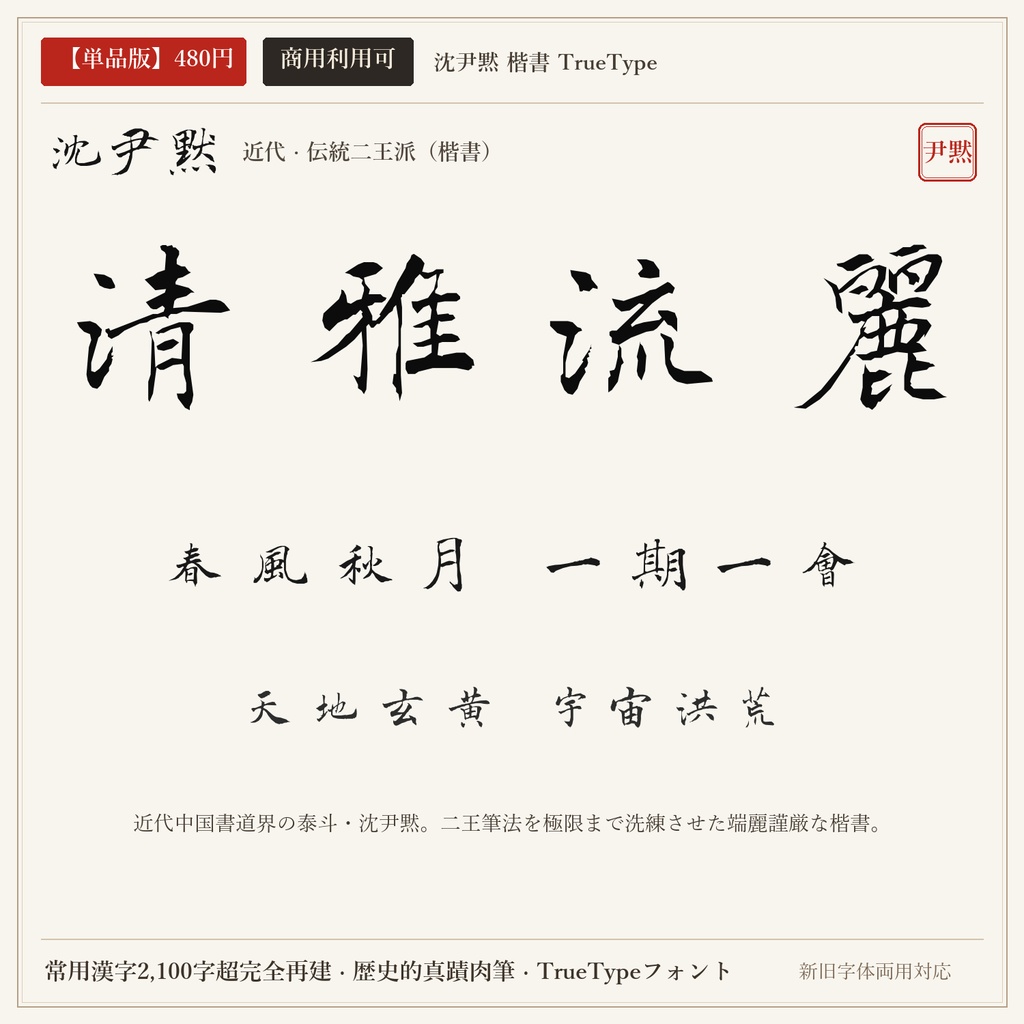
【単品版】沈尹黙 楷書フォント|近代の書聖・洗練された清雅・商用利用可
近代中国の最高峰の書家・沈尹黙の肉筆から制作したTrueTypeフォントです。魏晋の伝統筆法を徹底的に究め、近代的な清潔感と格調高い筆法を兼ね備えています。 ■ 本フォントの特徴 ・常用漢字2,136字中、2119字を高精度収録(網羅率 99.2%)。 ・現代の新字体を入力しても、歴史的な真蹟字形・旧字体が自然に出力されるデュアルマッピング対応。 ・文字ごとの最適なプロポーショナル字幅設定により、自然で流麗な連綿と墨の息遣いを再現。 ・トウフ(文字化け□)を出さない事前フォントマッピング検証済み。 ■ 未収録文字一覧(全17字) 歴史的真蹟・拓本に存在しない以下の字種は未収録(非対応)となります。ご購入前にご確認ください。 丼 厘 峠 扱 拶 枠 栃 桁 濫 碁 線 脊 著 込 郷 闘 駄 ■ 形式 TrueTypeフォント(TTF) / Windows・macOS両対応 ■ 利用規約 個人・法人の商用利用OK。クレジット表記不要。 ロゴ、動画、ゲーム、書籍、同人誌、配信サムネイル、Web、印刷物、グッズ等に自由にご使用いただけます。 フォントファイル自体の再配布・共有・販売・転売は禁止です。 ※東晋の王羲之(行書)と盛唐の顔真卿(楷書)を同梱した「【無料版】王羲之 + 顔真卿 2書体セット(0円)」もショップ内にて無料配布中です。